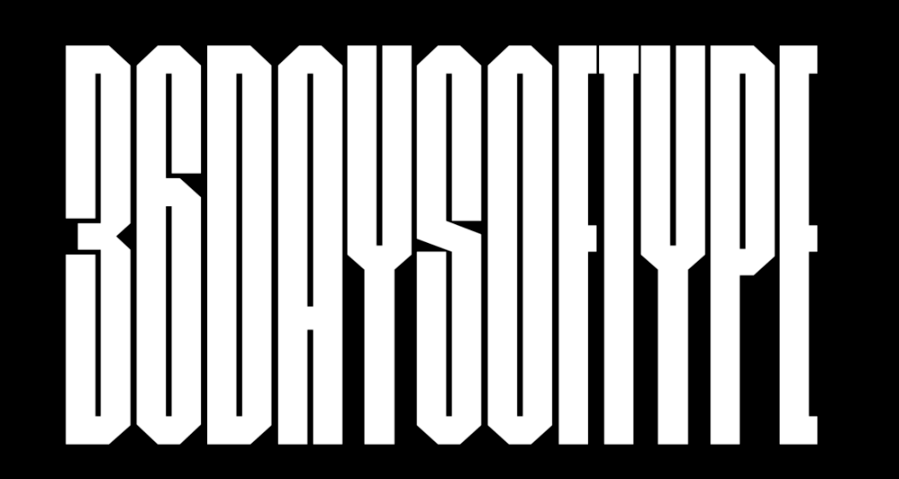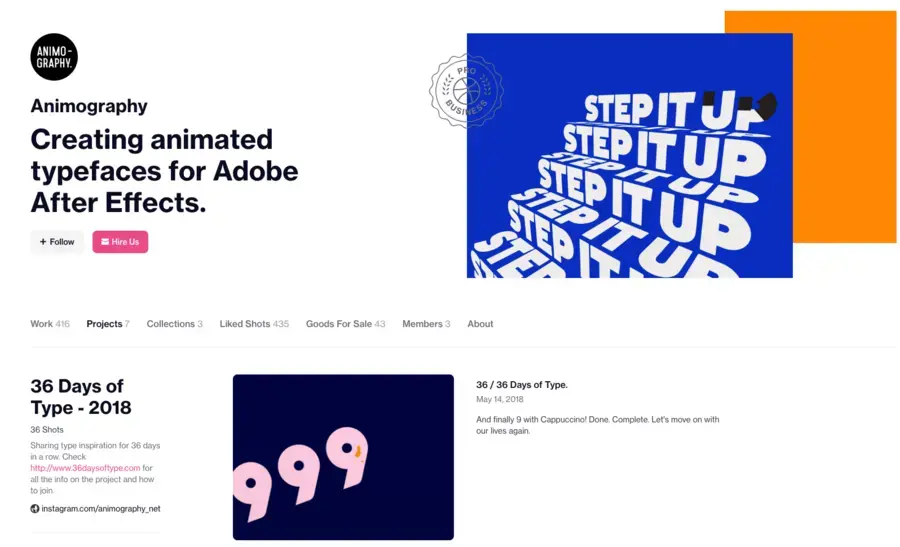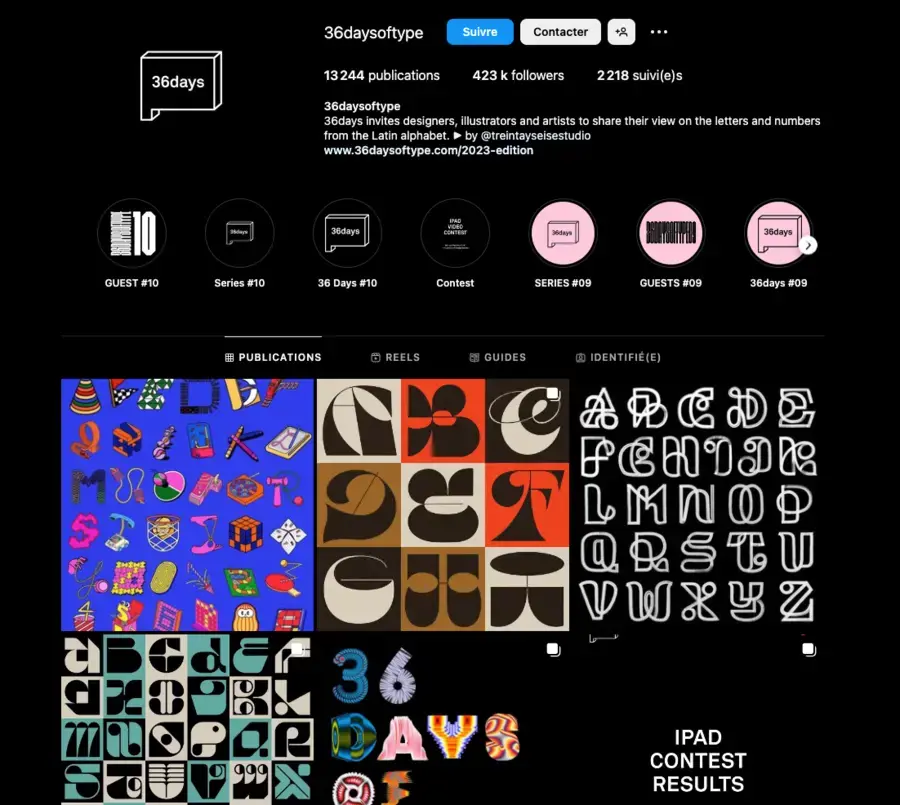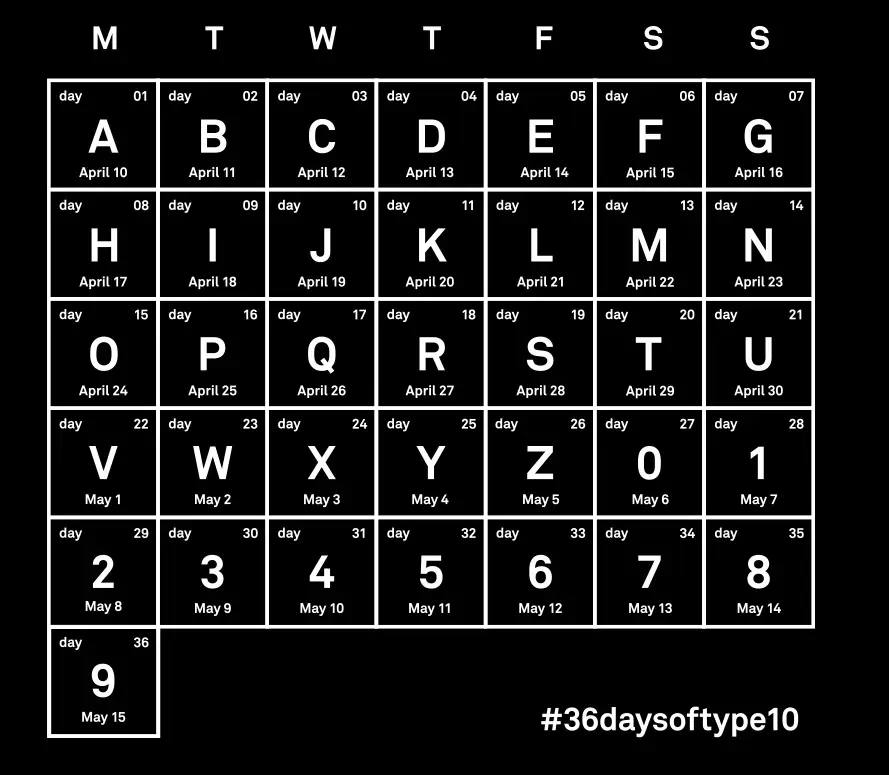
36 jours pour donner du caractère à vos créations
36 jours pour laisser place à votre créativité et à la typographie – 36 Days of type
Aujourd'hui, nous vous proposons de découvrir une idée intéressante pour partager sa créativité autour de la typographie avec la 5ème édition de 36 Days of type.
36 days of type
36 jours pour donner du caractère à vos créations
On voit régulièrement des designers se donner des défis personnels afin de faire une réalisation par jour ou par semaine sur un thème défini. Cela donne un excellent exercice pour progresser rapidement et gagner en expérience. Le projet 36 days of type est basé sur ce concept, mais avec une ouverture sur le monde entier, en invitant des designers, illustrateurs et artistes à exprimer leur créativité sur des chiffres et lettres de l’alphabet. On retrouve sur le site l'ensemble des explications avec un tableau périodique pour les lettres à imaginer chaque jour de A à Z et de 0 à 9.
Imaginer lettre chaque jour
Vous pouvez découvrir les différentes créations à l'aide du hastag #36daysoftype sur les différents réseaux sociaux.
Il y a également un compte Instagram officiel qui regroupe les créations sélectionnées des studios invités et designers.
Compte instagram 36 days of type
Cette année il y a également le groupe Animography qui participe au défi et le résultat donne une bonne dose d'inspiration pour l'animation typographique.
Animography 36 days of type